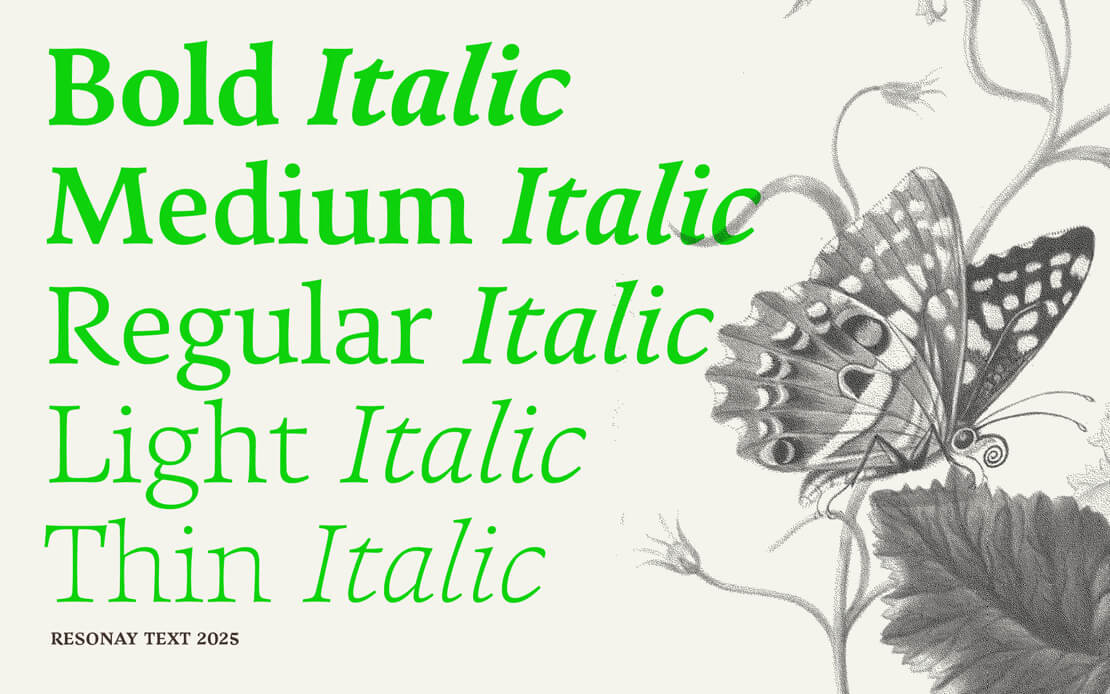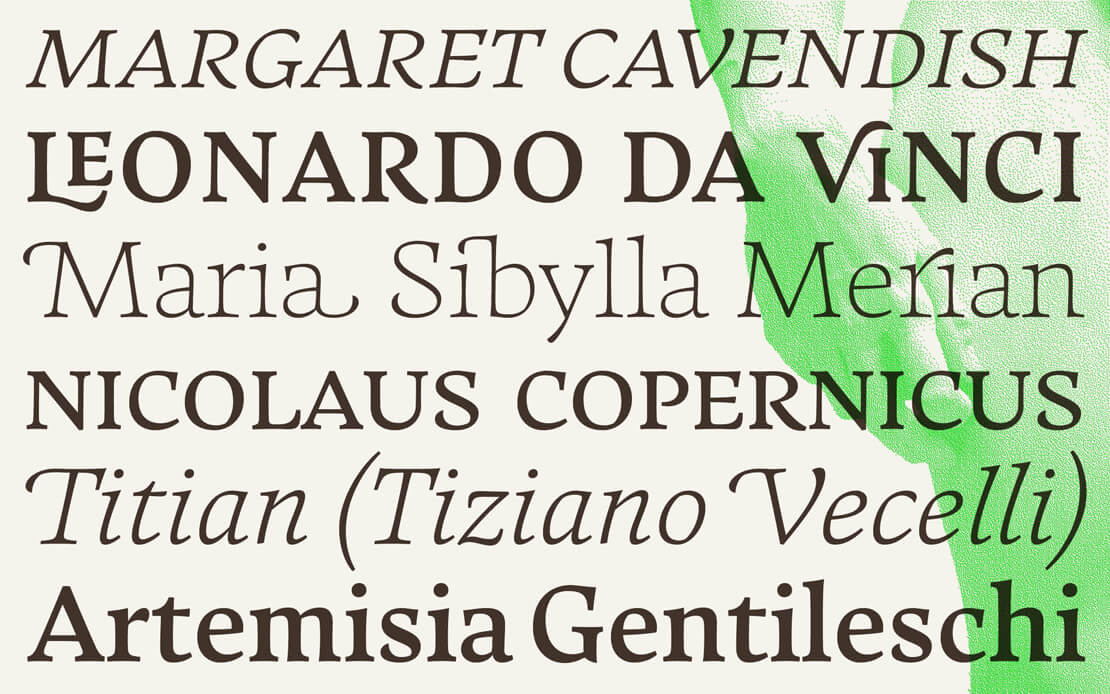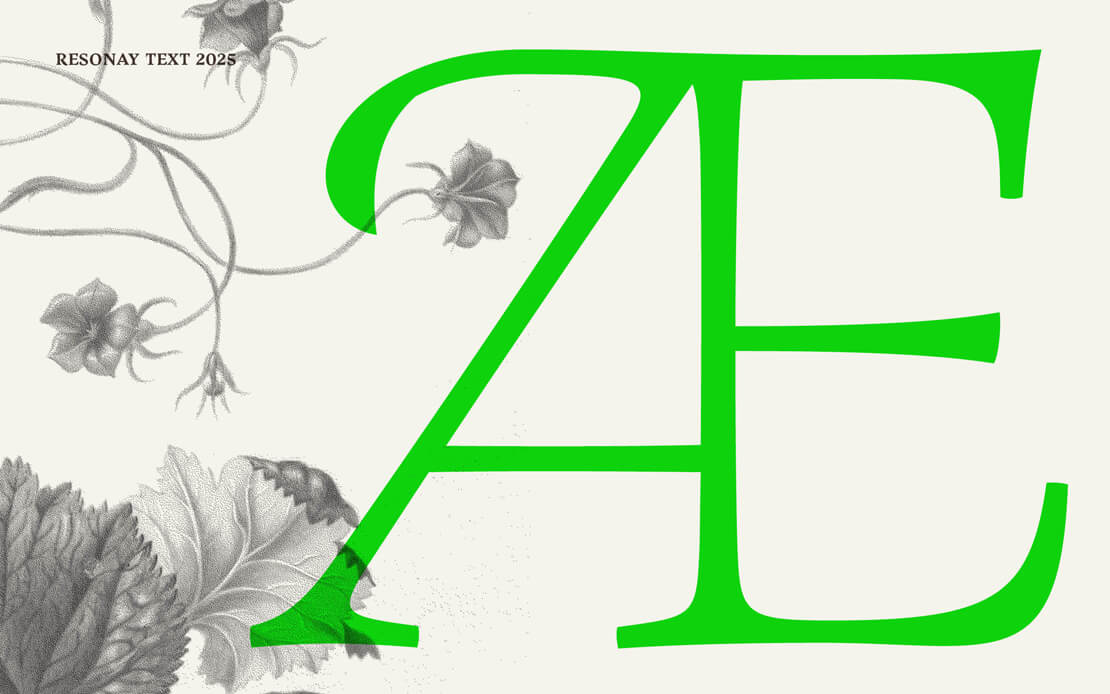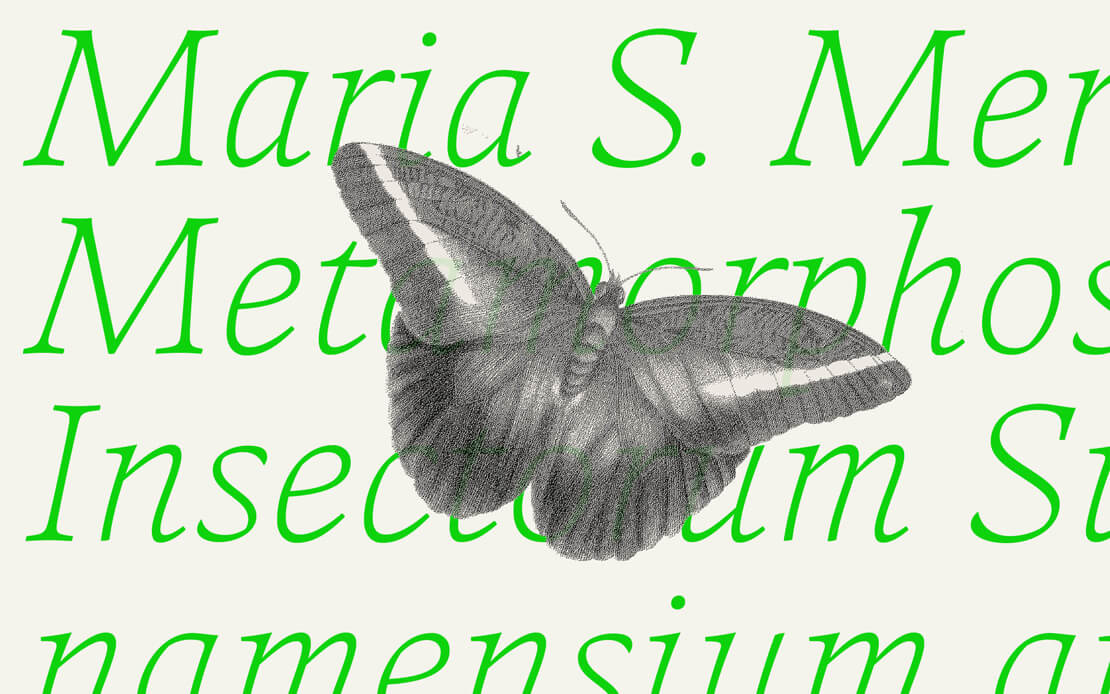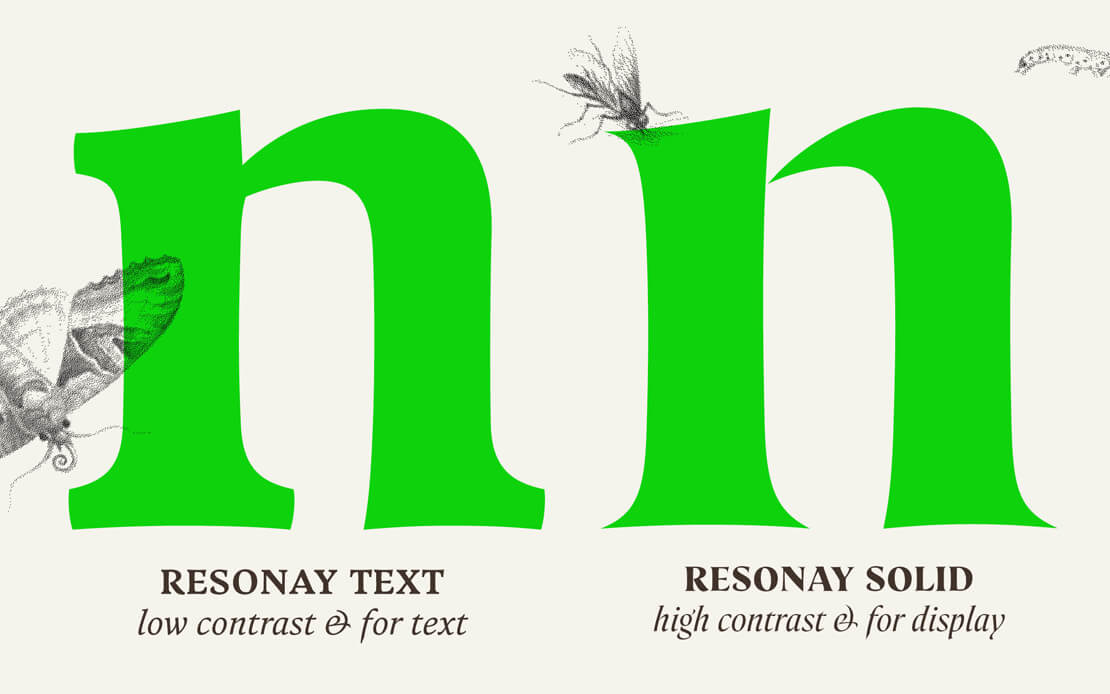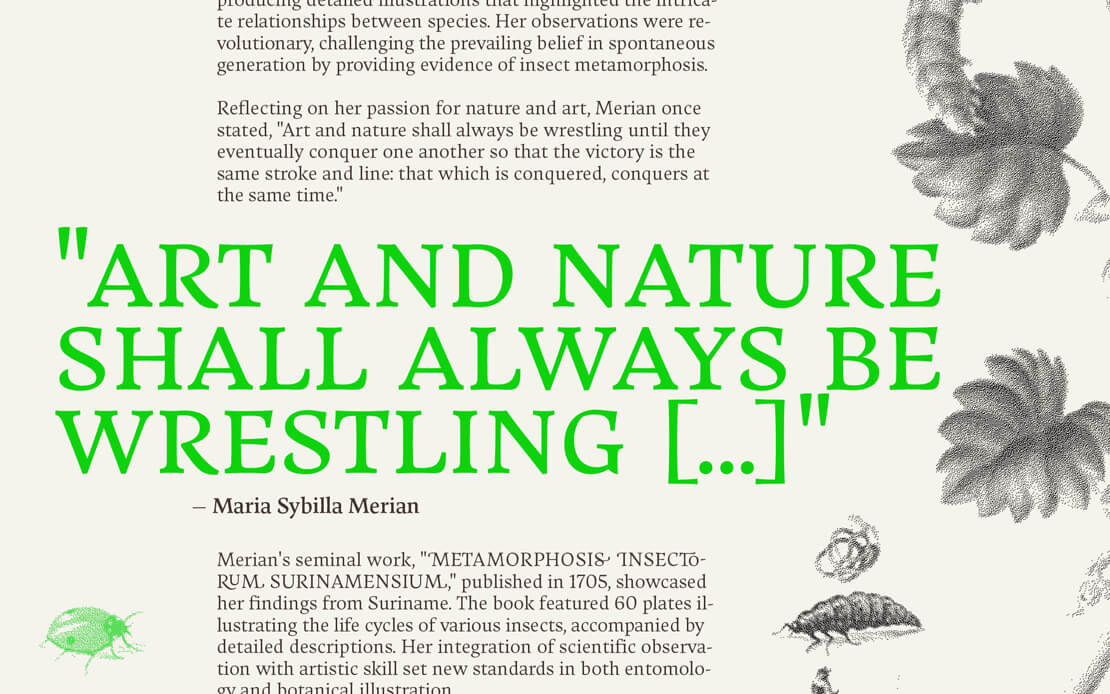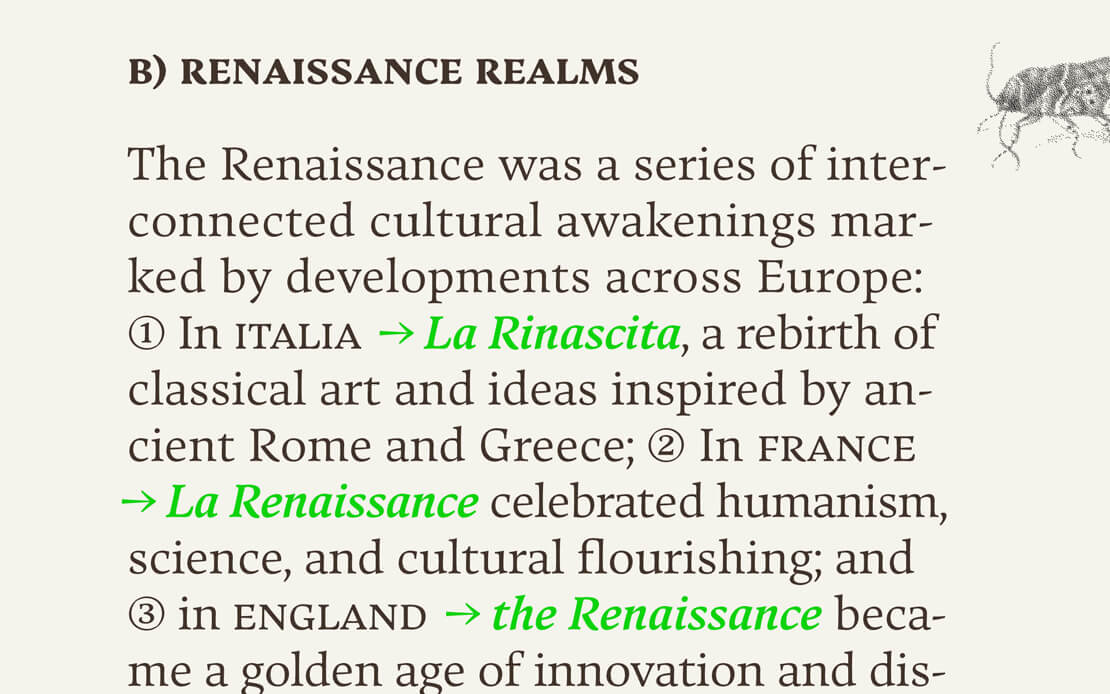
Resonay Text: Typografie mit poetischer Note
Die Typefoundry TypeMates stellt mit »Resonay Text« die neueste Erweiterung der Schriftfamilie »Resonay« vor. Die Schrift wurde speziell für Fließtexte entwickelt und verbindet klassische Buchstabenformen mit klarer Lesefreundlichkeit, geschwungenen Linien und kunstvollen Details, die an Steinmetzarbeiten erinnern.
Resonay Text
Im Zentrum der neuen Schrift von Andrej Dieneš stehen klassische Typografie und vielseitige Gestaltungsmöglichkeiten. Resonay Text bietet unter anderem Kapitälchen, Versal-Ligaturen und eine Vielzahl an Schwungbuchstaben, die Wortanfänge und -enden hervorheben. Mit ihrer kalligrafischen Ausrichtung eignet sie sich zudem auch für poetische Texte und verspielte Zitate.
Einige Sonderzeichen der Schrift Resonay Text
Ein weiteres Merkmal sind die in der Kursiven enthaltenen Initial-Formen der Versalien. Darüber hinaus umfasst die Schrift echte Kapitälchen sowie stilistische Varianten für Ziffern und Mediävalziffern. Durch die OpenType-Technologie passen sich die Satzzeichen automatisch dem gewählten Stil an.
Resonay Text Schriftmuster
Technische Details und Funktionen
Resonay Text bietet fünf Gewichte von »Thin« bis »Bold«, ergänzt durch entsprechende Kursive. Mit mehr als 2.000 Glyphen und einer Unterstützung für über 200 lateinische Sprachen deckt die Schrift viele Anforderungen anspruchsvoller Typografie ab. Hoch- und tiefgestellte Buchstaben sowie umfangreiche Symbolsammlungen ergänzen die Vielseitigkeit der Schrift in Print- und digitalen Medien.